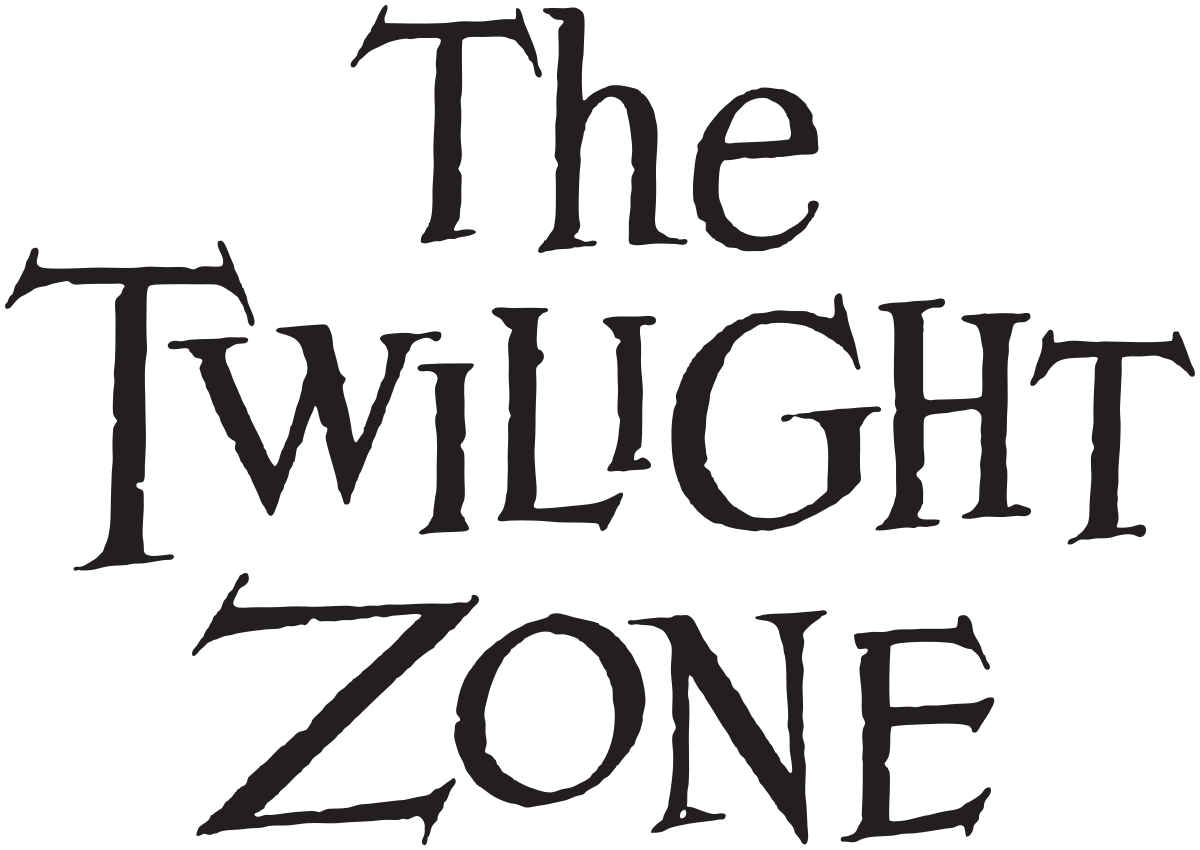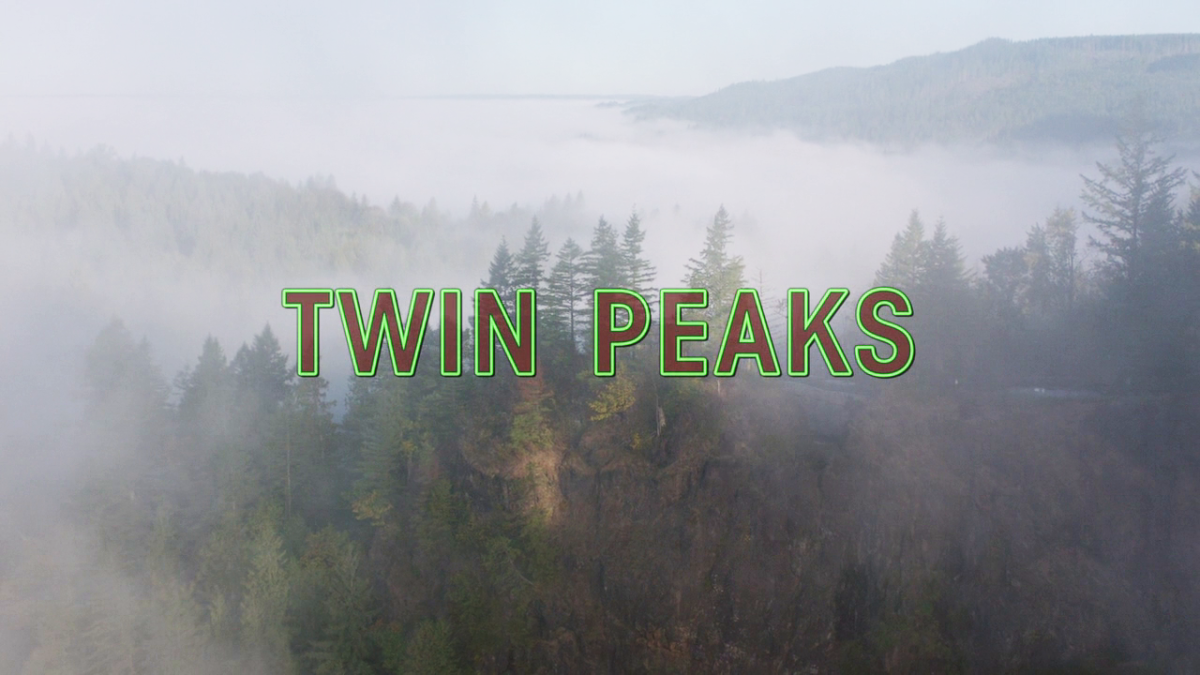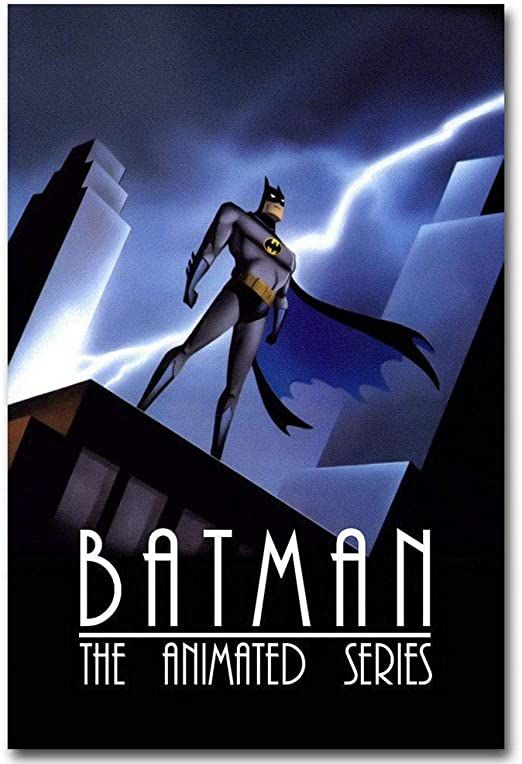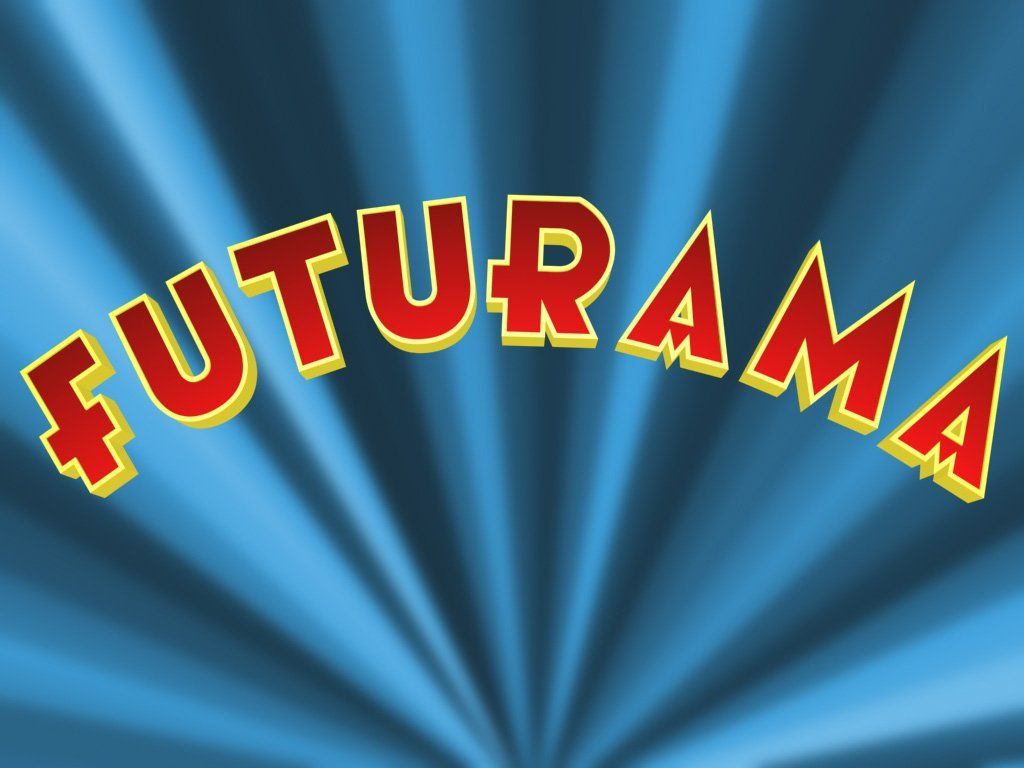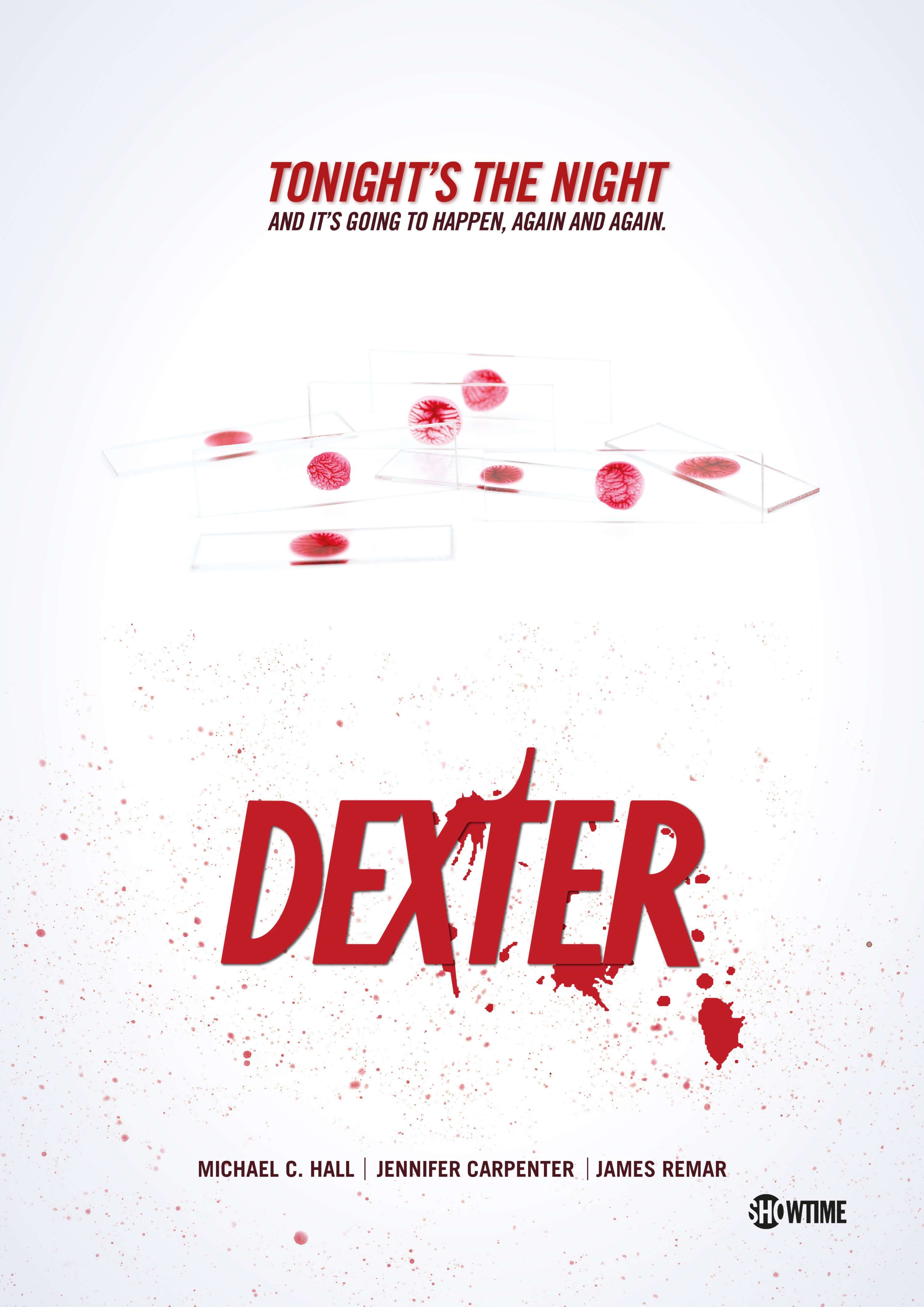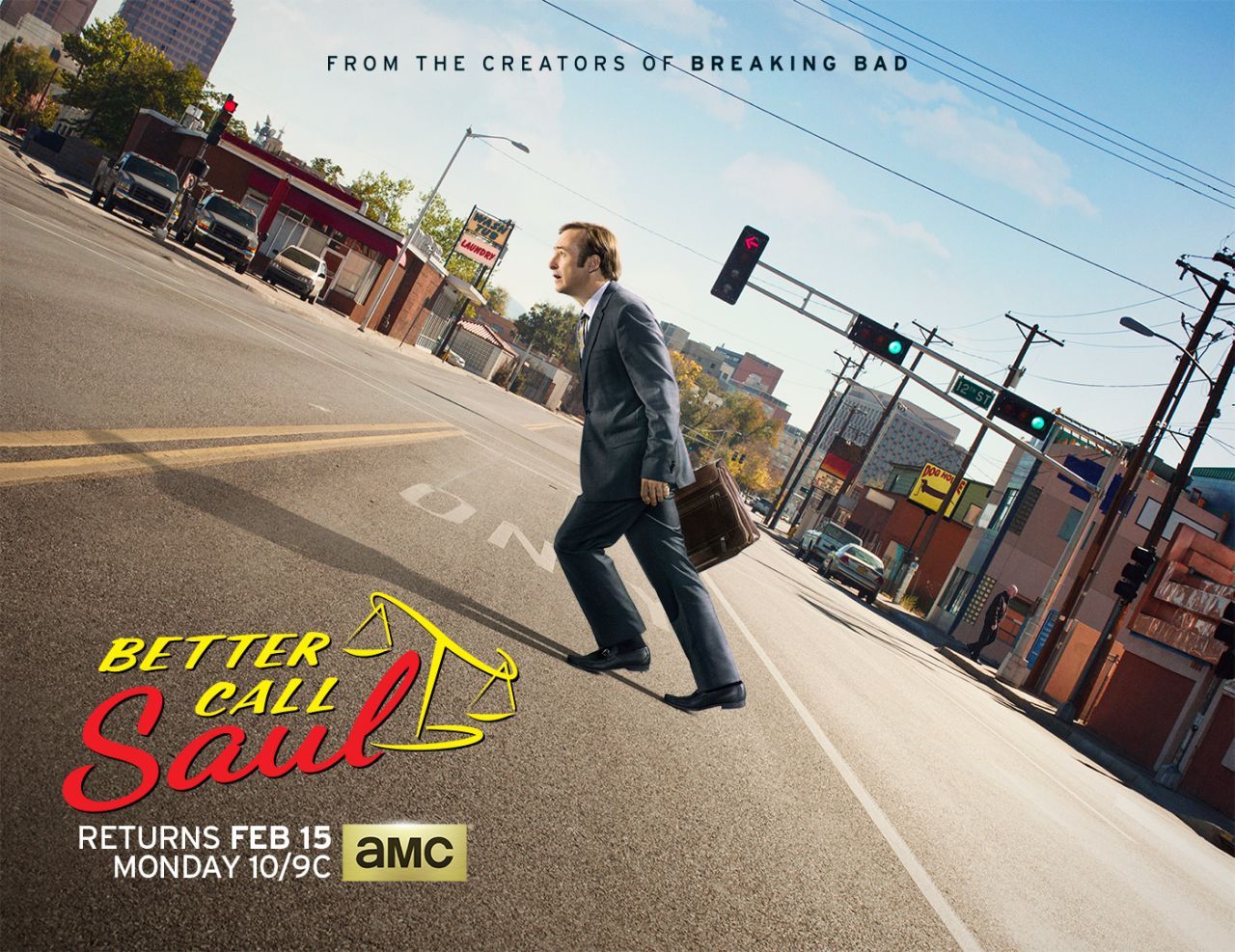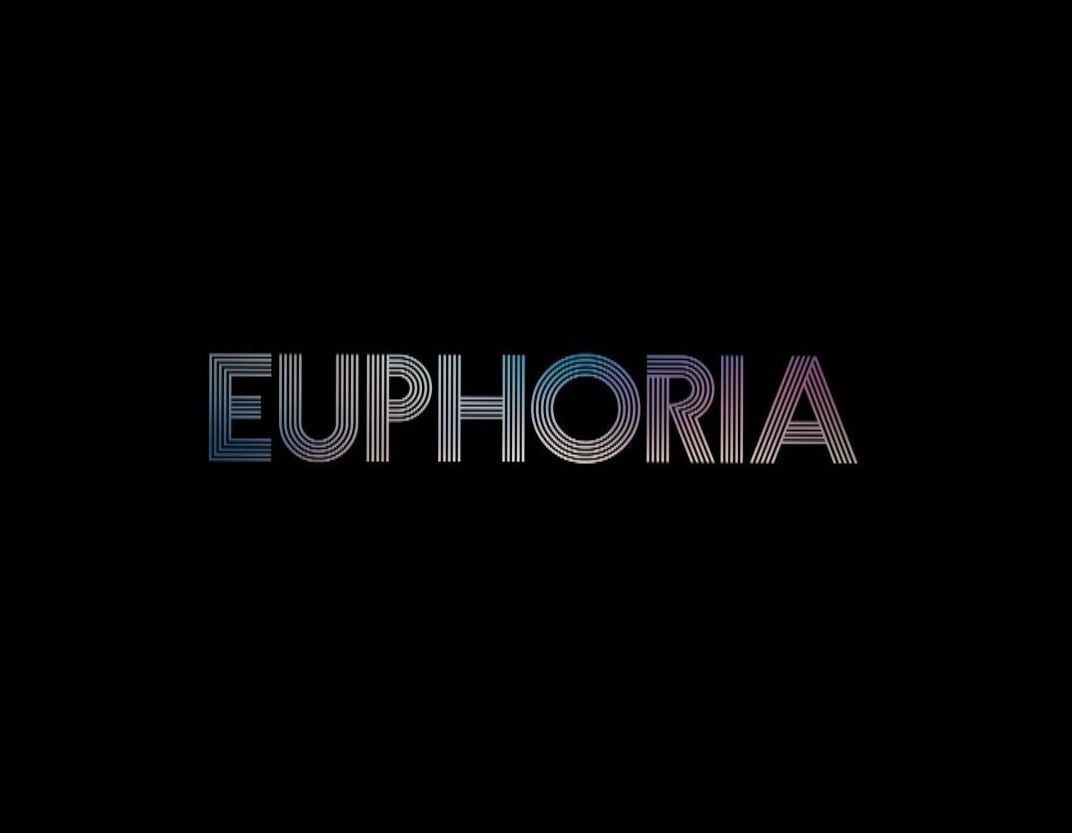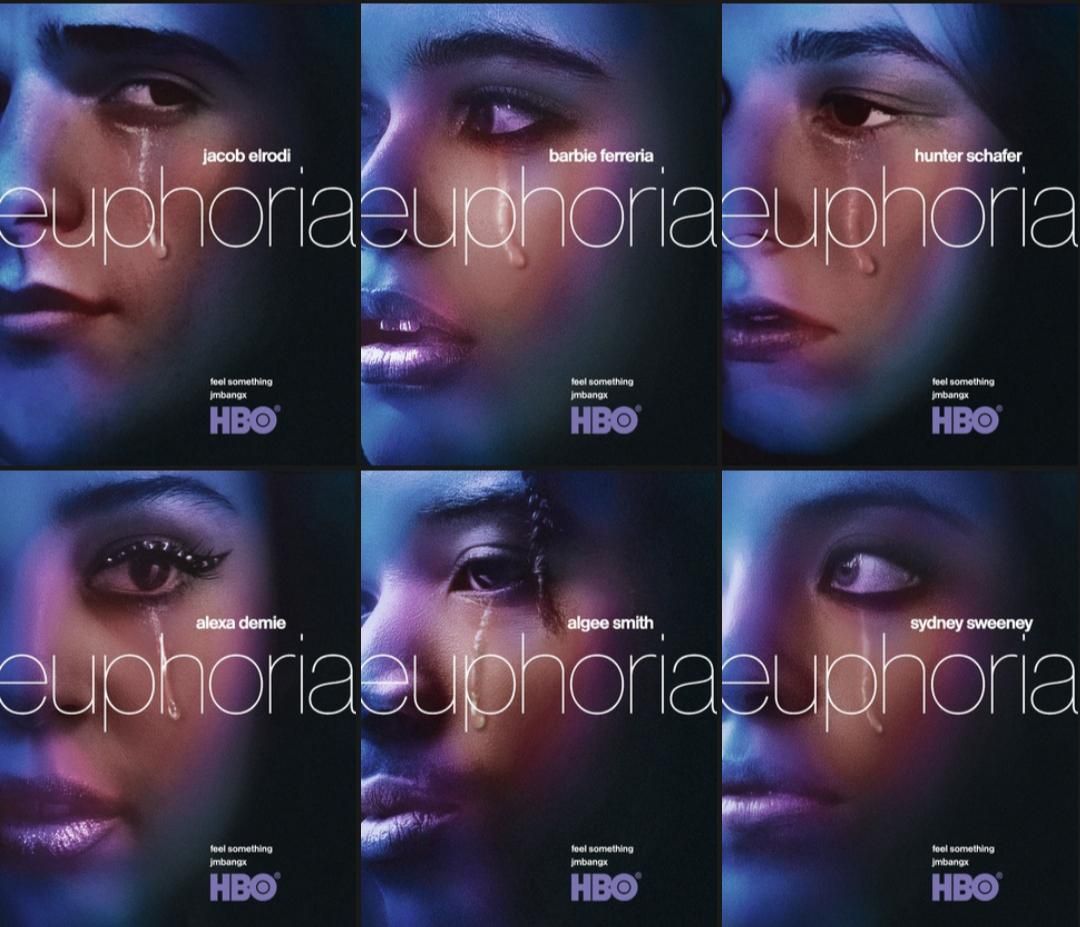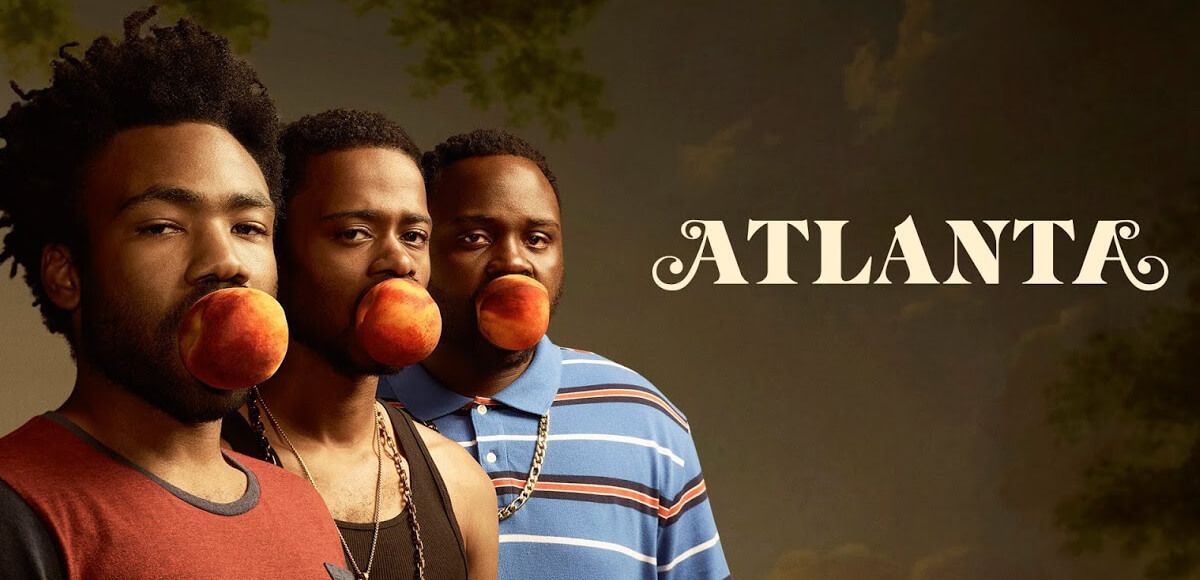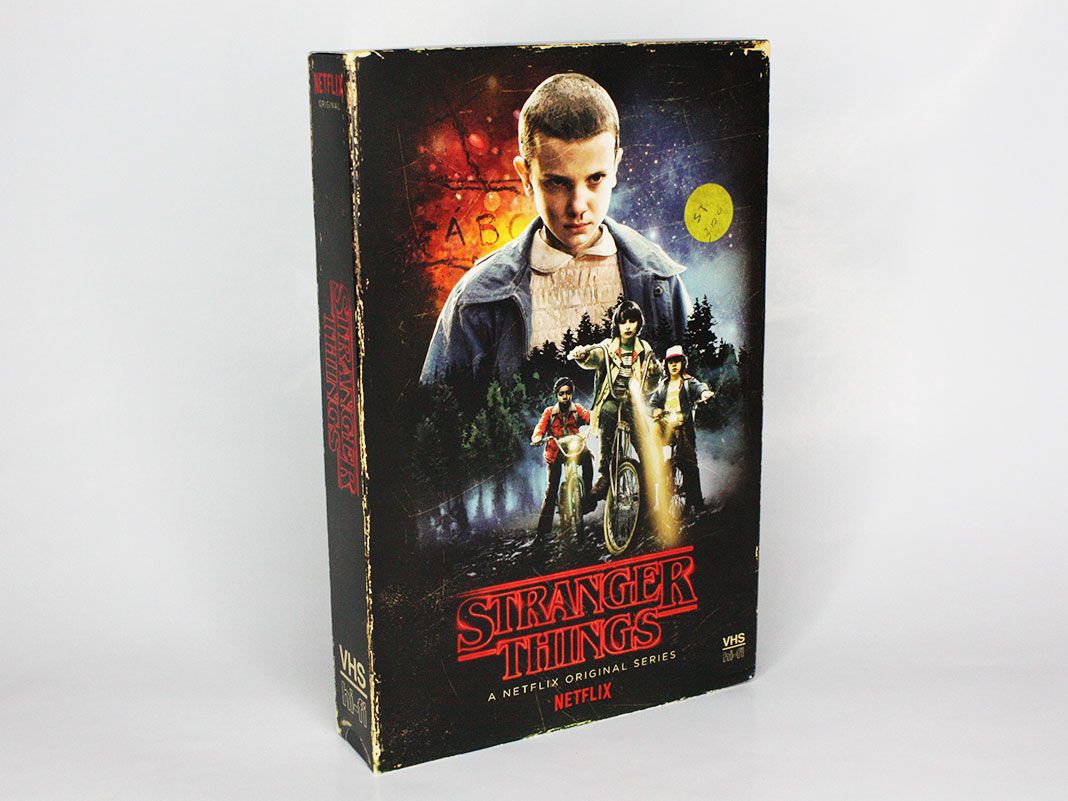
Top 10: Tipografías de series de televisión
Conoce algunas tipografías que se han usado en los títulos de las series televisas de distintas épocas
Muchas veces recordamos una serie de televisión por escenas impactantes o personajes entrañables. También cuando escuchamos la música de sus introducciones, y por arte de magia nos remontamos a la primera vez que las vimos.
En esta lista recopilamos algunas de las tipografías que acompañan las secuencias, así como el material promocional, de series inolvidables a través del tiempo.
The Twilight Zone (1959-1964)
Una serie clásica que sentó las bases de la televisión de fantasía, ciencia ficción, thriller y terror. El logotipo inconfundible hacía referencia a esta sensación de angustia y misterio, desde luego, acompañado por el tema musical de Marius Constant.
Tipografías: Bernhard Mod., Venus
Astro Boy (1980)
La segunda aparición en televisión de este personaje, después de la serie en blanco y negro de los años sesenta. La tipografía es obra de los diseñadores Ronné Bonder y Tom Carnase, lanzada en 1970. Una estilización de esta tipografía se usó famosamente en el soundtrack de Shaft por Isaac Hayes, pero inevitablemente la asociamos con robots.
Tipografía: ITC Pioneer.
Twin Peaks (1990-1991)
Una de las introducciones de la televisión más célebres, lo mismo por su tema musical que por las imágenes. El diseño es de Pacific Title, donde las imágenes sepia del bosque contrastan con la tipografía verde brillante. De acuerdo con el coceador Mark Frost, esta secuencia “te dejaba boquiabierto”. David Lynch repitió la estética en el regreso de la serie en 2017.
Tipografías: ITC Avant Garde Gothic
Batman: la serie animada (1992-1993)
Los productores Bruce Time y Eric Radomski quisieron darle a la serie una atmósfera noir, similar a la de las dos películas de Tim Burton, con una influencia del art déco y los años treinta y cuarenta.
Tipografías: Plaza, Empire, Present, Kaptiva
Futurama (1999-2013)
El logotipo fue dibujado a mano, y tanto el título como la intriducción y se inspiraron en el art déco y en los parques de diversiones Tomorrowland de Disney. El producto final da una idea de retrofuturismo. Los diseñadores son Geraldine Symon, Scott Vanzo, Eric Whited, Conan Low y Mike Smith.
Tipografías: ITC Kabel, Insignia
Dexter (2006-2013)
Una espectacular secuencia de introducción (por la cual la agencia Digital Kitchen recibió un Emmy), que combina elementos de la vida cotidiana con motivos sangrientos. El logo parte de la tipografía de Zuzana Lucko, con el detalle de la letra T en forma de una cuchilla.
Tipografías: Soda Script, DIN 1451
Better Call Saul (2015- )
Este spin off de Breaking Bad ha sido universalmente aclamado por la crítica. Cada episodio usa el logotipo con efecto low-fi, referente a los vídeos VHS. El objetivo era crear un logo con una estética barata y de mal gusto, propia de los anuncios clasificados.
Tipografías: Script Casual, Dancing Script, VCR OSD Mono
Atlanta (2016- )
Este aclamado drama/comedia negra usa el logo integrado creativamente en distintos paisajes de la ciudad. Se caracteriza por el uso en espejo de las letras A del inicio y del final, y se inspira en la tipografía Benguiat Calson.
Tipografía: Cabernet
Stranger Things (2016- )
Esta serie de ficción y misterio es un homenaje a la cultura popular de los ochenta. La secuencia del título, completamente tipográfica, es un diseño de la agencia Imaginary Forces, en la que se aparecen las letras con la música para producir una sensación angustiante. El logotipo se inspiró en las portadas de los libros de Stephen King y en los diseños de Richard Greenber, que trabajó en películas como The Goonies.
Tipografías: ITC Benguiat, ITC Avant Garde Gothic
Euphoria (2019- )
Caracterizada por una paleta de colores neón, reflejada tanto en el maquillaje y la ropa como en las múltiples escenas de la vida nocturna, esta serie de HBO usó un logo customizado. Con un gradiente neón de cinco líneas, se basa principalmente en la tipografía Prismaset de Lineto. Para otras aplicaciones se usaron tipografías minúsculas.
Tipografías: Prismaset, Eeuw Haas Gr., Motter Ombra (soundtrack)